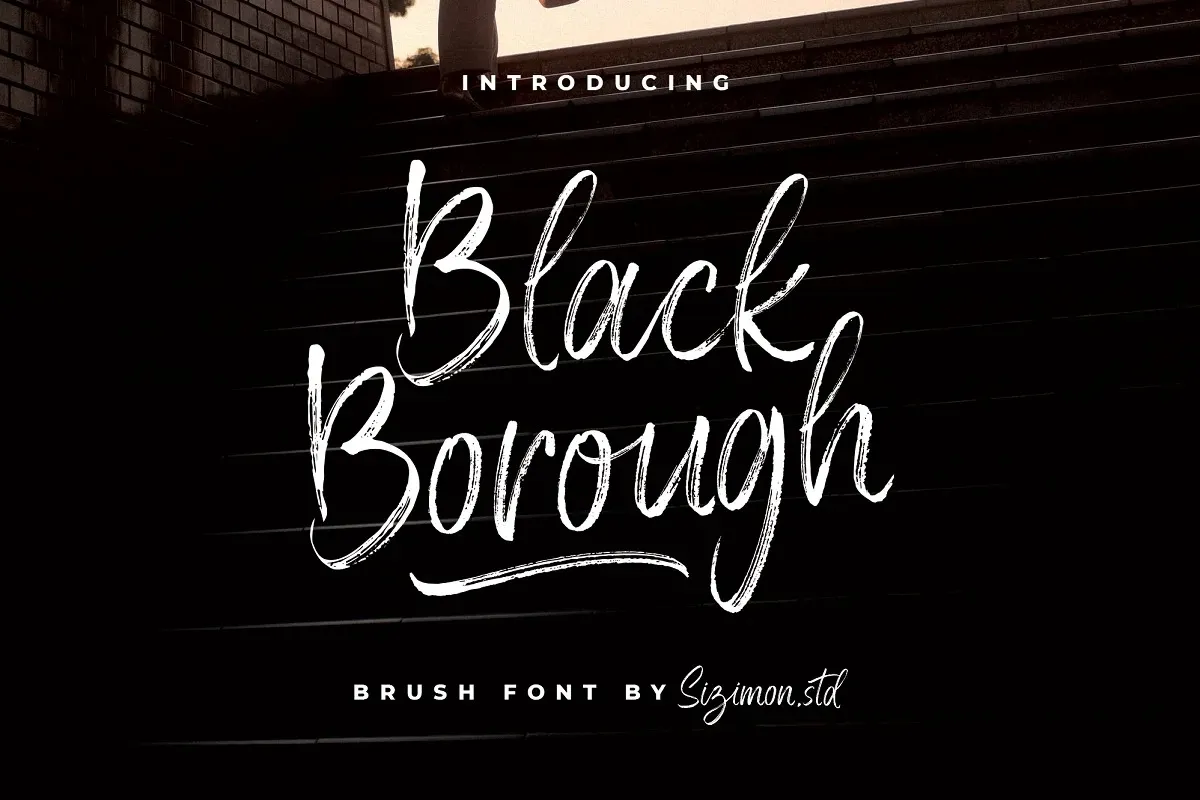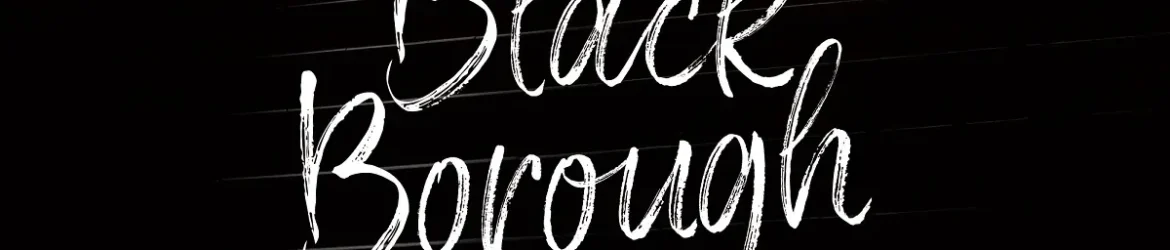
Black Borough Font – Download Grátis
A fonte Black Borough Font é uma escolha perfeita para designers que buscam um estilo elegante e autêntico. Desenvolvida por sizimon, essa brush font apresenta textura única que transmite um script sofisticado. O resultado é um estilo de letra capaz de destacar qualquer projeto, especialmente em elementos como logotipos, tags de nomes, citações escritas a mão e embalagens de produtos. Ideal para a criação rápida de designs de etiquetas para produto, materiais de merchandising e até mesmo cartões de felicitações e conteúdo para redes sociais. É versátil o suficiente para atender a uma variedade ampla de necessidades gráficas, desde logos profissionais até produtos customizados de maneira rápida e eficaz, graças à sua extensa gama de letras maiúsculas e minúsculas, pontuação e números. Além disso, oferece suporte multilíngue para atender aos mais diversos públicos consumidores. Com Black Borough Font, a escolha certa torna-se um processo simples e imediatamente gratificante.